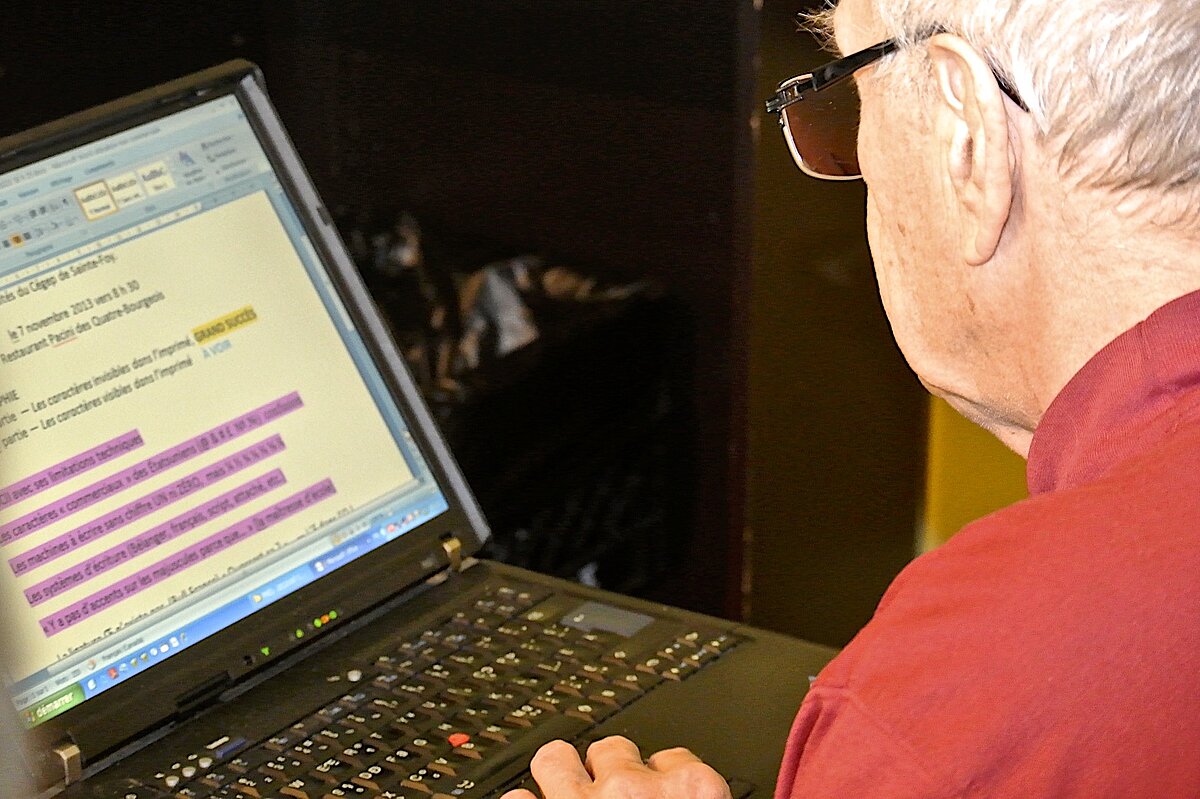
2013-11-07 - La typographie
Jean BEAUDOIN, géographe globetrotter, nous entretiendra de sa passion : la typographie et ses règles incluant le corps, la police, l’espace féminine tant visible qu’invisible. Vous pouvez consulter le résumé de sa présentation ci-dessous.
L'ASCII avec ses limitations techniques :
- Les caractères « commerciaux » des Étatsuniens (@ # £ &) et Nº
- Les machines à écrire sans chiffre UN ni ZÉRO, mais ¼½¾????
- Les systèmes d'écriture (Bélanger, français, script, attaché, etc.)
- « Y a pas d'accents sur les majuscules parce que... » [la maîtresse]
- La ligature O n'existe pas. (Bull France) « Quossest ça » ? L'E dans l'O !
- Les points sur les zis zé les jis. (Le JARD?N MOB?LE)
- La fonction titre (title /taï.toul/) dans Word®, PageMaker® et ses méfaits
- Les minuscules et les MAJUSCULES c’est la même confusion.
L'infographiste qui s'éclate tue les normes ISO et les standards contraignants comme le dictionnaire, la grammaire, les lois et les règlements, il fait plein de fautes. (Radio-Canada, TVA, V) 20H HE HA
Nombreuses photographies récentes des dégâts déjà faits, juste avant que nous passions au mandarin, si ce n'est pas d'abord par l’écriture.